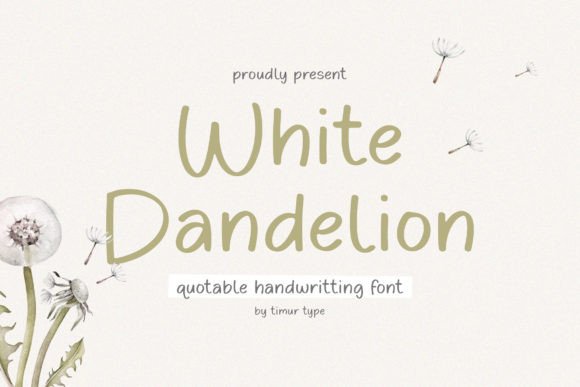
White Dandelion
適切なデザイン要素を見つけるのは難しい場合がありますが、White Dandelionは作品を即座に引き立てる優れたコレクションを提供します。
精密に作られたWhite Dandelionは、クリーンなベクター、滑らかなタイポグラフィ、そして安心のための商用ライセンスを提供します。
POD(オンデマンド印刷)製品、結婚式の招待状、またはソーシャルメディアのグラフィックを作成している場合でも、White Dandelionは理想的です。